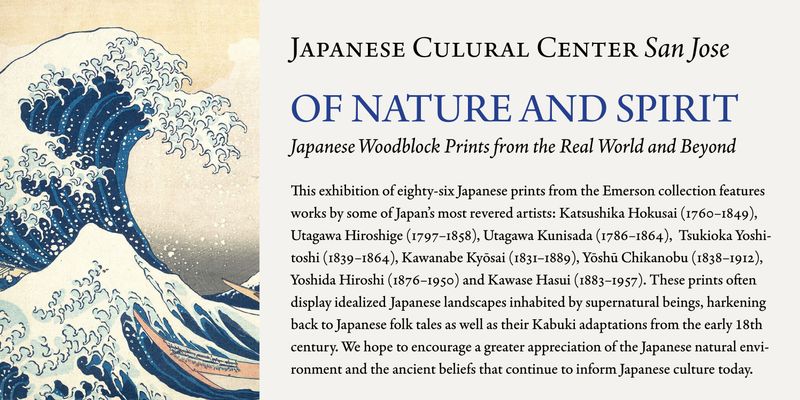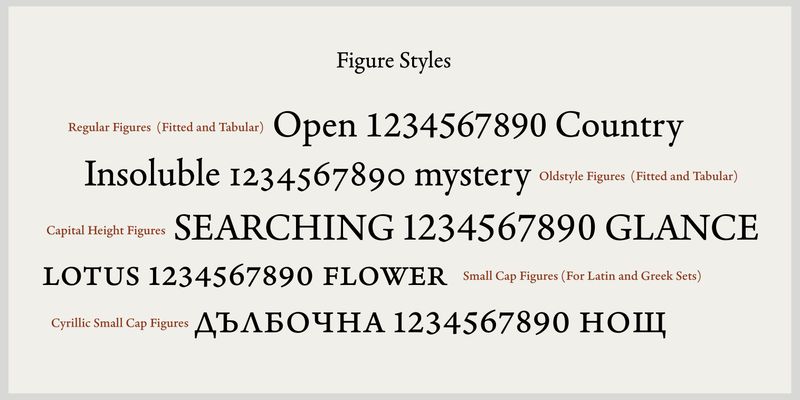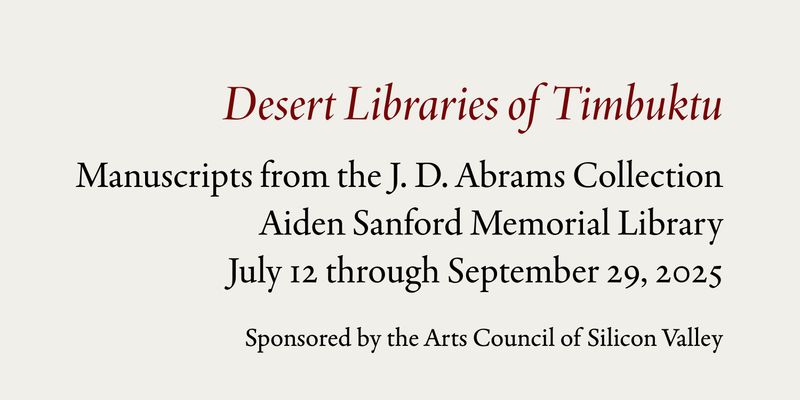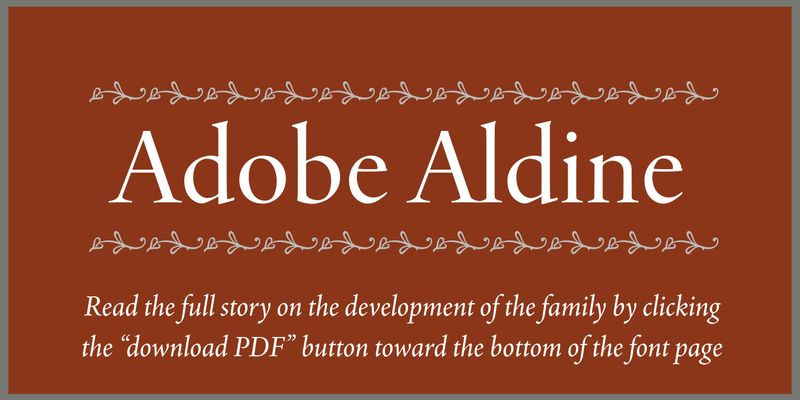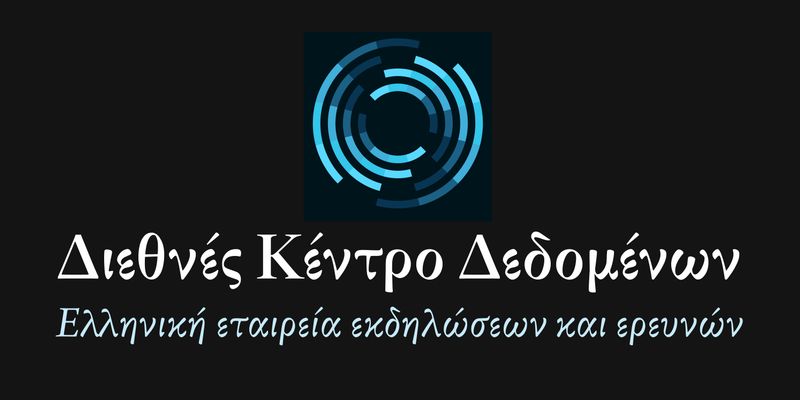
Después de muchos años de desarrollo, ¡por fin se ha lanzado el último tipo de letra de Adobe Originals del ilustre diseñador tipográfico Robert Slimbach! Aldine es una interpretación contemporánea de los tipos de letra de los libros humanistas desarrollados en Aldine Press a principios del siglo XV.
Se completa con la cobertura de idiomas para latín, griego y cirílico, así como varios estilos de cifras y adornos preciosos. Está disponible en formato variable y estático, y brinda a los diseñadores la capacidad de crear fuentes personalizadas en cualquier combinación de grosor y tamaño óptico.
Adobe Aldine se ha diseñado teniendo en cuenta el uso en pantalla, ofreciendo un sistema coordinado de tipos de letra altamente legibles que traen textos clásicos del pasado y los adaptan a los entornos de trabajo digitales modernos.
El programa Adobe Originals se inició en 1989 como tipográfica interna de Adobe, creado para desarrollar tipos de letra originales con una calidad de diseño ejemplar, fidelidad técnica y longevidad estética.
En la actualidad, la misión del equipo de Type es crear tipos de letra sofisticados e incluso experimentales que exploren las posibilidades del diseño y la tecnología. Los tipos de letra que se publican como originales de Adobe son el resultado de años de trabajo y estudio, y se consideran estándares del sector por la ambición y la calidad de su desarrollo.